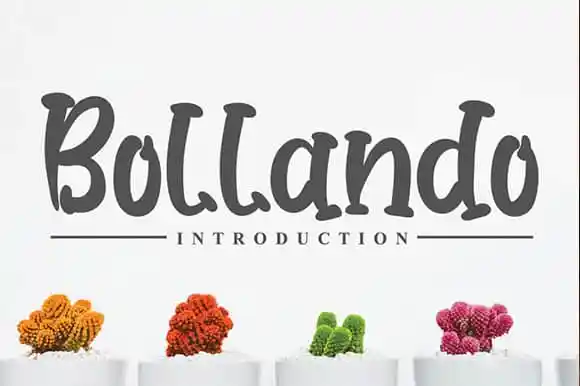
Bollando Displays Font – Download Grátis
A fonte Bollando Displays é a escolha perfeita para qualquer projeto que exija graça e estilo. Seja uma publicidade criativa para redes sociais, embalagens de produtos originais ou até mesmo cartões de visita elegantes. Esta serifada font foi projetada com destaque para o seu uso em displays de paredes e convites de casamento, mas também se adequa a muitos outros tipos de trabalho gráfico, como design fotográfico, marcas de imagem e muito mais. Adicionalmente, Bollando Displays oferece um toque de autêntica mão escritora que torna seu uso ainda mais versátil. Esta font é ideal para aqueles em busca de uma solução criativa e diferenciada, seja para o próximo projeto gráfico ou site. O resultado é uma combinação única que mantém a simplicidade do estilo serifado com um toque único de modernidade e personalização.